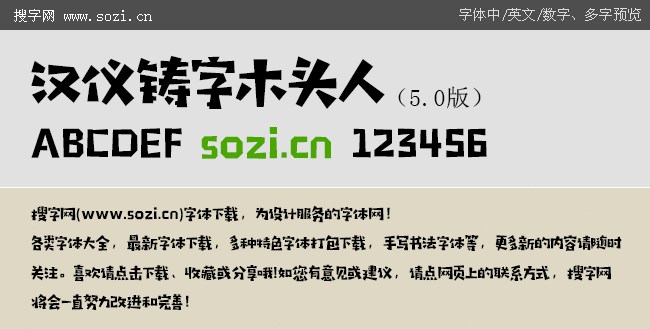
漢儀鑄字木頭人
搜字網(wǎng)提供一款漢儀鑄字木頭人中文藝術(shù)字體下載,漢儀鑄字木頭人是一款卡通風(fēng)格的字體,親切、俏皮、輕松、活潑的字形,感覺像極了游戲“1.2.3 木頭人”,筆畫粗重,趣味性強(qiáng),可用于藝術(shù)設(shè)計(jì)、包裝印刷、圖形設(shè)計(jì)等領(lǐng)域。設(shè)計(jì)師們過節(jié)玩兒游戲,來和這款字體一起愉快的玩耍吧!